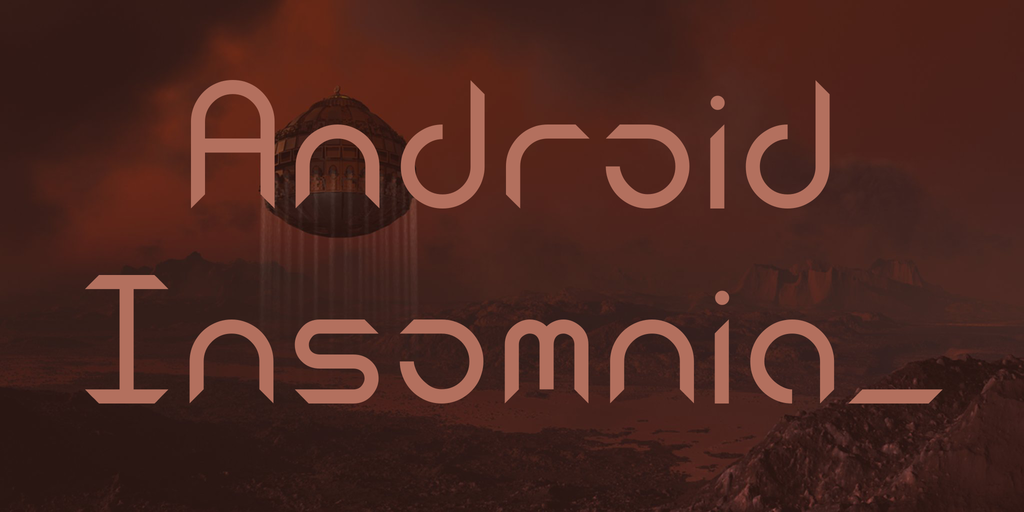
A Android Insomnia Font é uma elegante seleção do mundo dos sonhos insomnicios nos mundos tecnológicos. Inspirada no estilo Blackletter, esta fonte foi criada pelo designer Hamilton utilizando a Birdfont, um software para desenhar e editar modelos tridimensionais de forma intuitiva, desenvolvido por Johan Mattsson. Lançada em 24 de setembro de 2015, essa fonte apresenta nuances interessantes do mundo da programação e da tecnologia que não encontramos em outras fontes de linguagem. Como um complemento perfeito para os designers digitais, a Android Insomnia Font oferece um tom criativo e único capaz de destacar seus projetos, seja em aplicativos móveis ou sites. Seja você um programador ansioso pela noite ou simplesmente uma pessoa que aprecia o design tecnológico, esta fonte é certamente algo para se reunir.